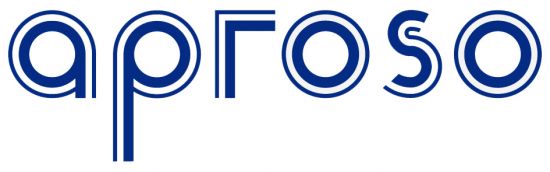
ich suche die Schrift von Logo unserer Firma.
sieht für mich nicht aus, als ob alle buchstaben aus einer schriftart stammen.
wenn ich das nachbauen sollte, würde ich als basis zum beispiel die horatio nehmen. ohne modifikationen:
vielleicht findet jemand die schrift mit diesem umrisstyp, aber ich glaube, auch der ist marke eigenbau.
Das ist recht schnell nachgebaut, schneller als die Schrift zu finden.
Soll es exakt so werden wie das Original, würde ich einfach von geometrischen Grundformen ausgehen.
Soll es etwas schöner werden, was ich anstreben würde (besonders beim s), ist thierrys Vorschlag eine gute Ausgangsbasis.
Vielleicht liegt es am Blau und am Weiß, mir drängt sich das kantige r als g auf: argos(o). Wenn du das Logo nicht nur nachbauen, sondern auch modifizieren darfst, dann mach das doch (so ähnlich wie Thierry es vorgeschlagen hat).